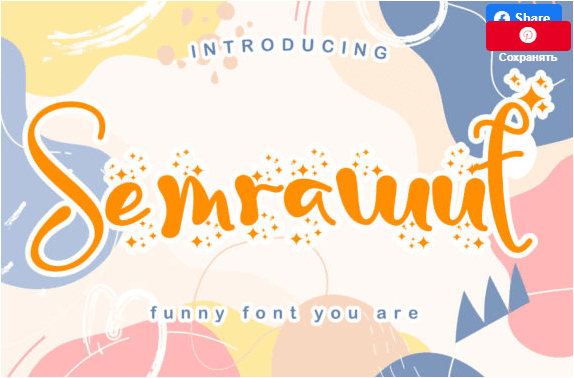
Semrawut Font
Semrawut — прекрасный и вневременной рукописный шрифт. Это лучший выбор для создания привлекательных логотипов, брендинга и цитат. Этот шрифт имеет кодировку PUA, что означает, что вы можете легко получить доступ ко всем глифам и росчеркам!